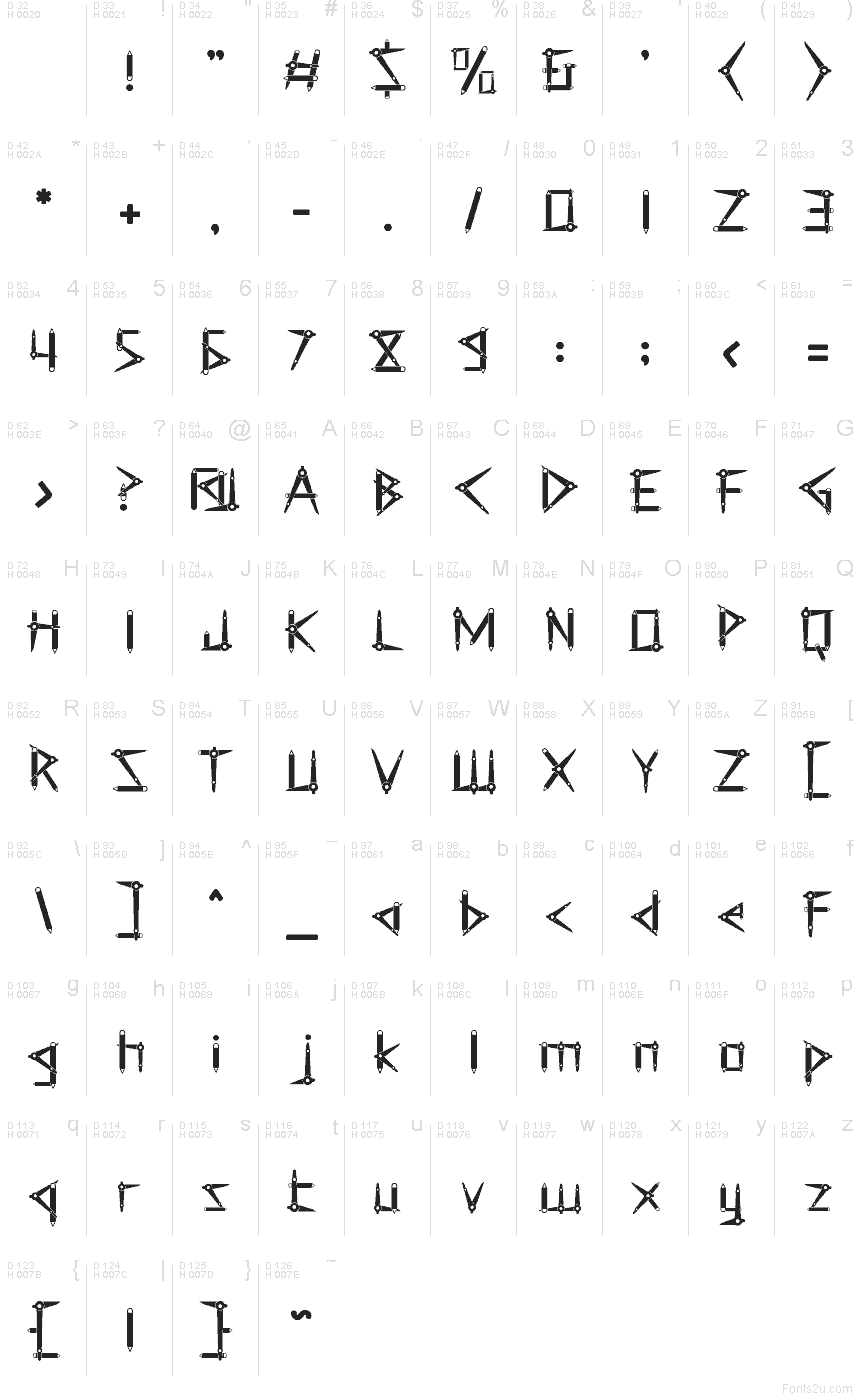
Clever Science Caliper
Clever Science Caliper von Putracetol Studio ist eine kostenlose Dingbat-Schrift, die technische Zeichenwerkzeuge in eine klare, schwarze Silhouette übersetzt. Das Design spielt mit Elementen wie Zirkelschenkeln, Bleistiften und metallischen Gelenken. Die präzisen Spitzen und kreisförmigen Drehpunkte lassen die gesamte Schrift wie aus einem Labor stammendes Equipment wirken.
Sie eignet sich hervorragend für STEM-Poster, Arbeitsblätter, Notizbuch-Cover, wissenschaftliche Projekte und Bildungs-Branding, bei dem eine Schriftart mehr als nur Buchstaben vermitteln soll. Die kompakten Werkzeug-Formen funktionieren zudem ideal für Badges, Kapitelanfänge oder kurze Titelkarten, wenn ein präziser, akademischer und gleichzeitig spielerischer Look gefragt ist.